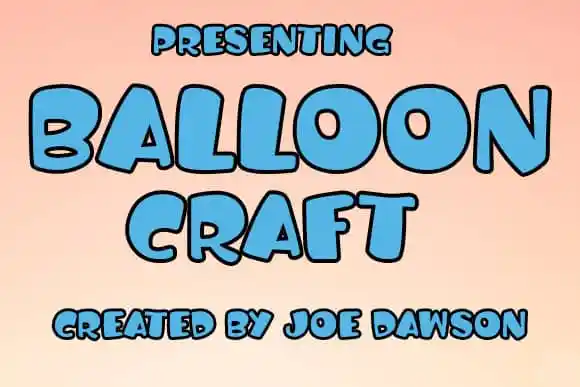
A ‘Balloon Craft Display Font’ é uma escolha perfeita para aqueles que buscam um tipo de exibição divertido e infantil para seus projetos de design. Desenvolvida pelo designer Joe Dawson na categoria de tipos de fontes de display, essa opção é ideal para adicioná-la a qualquer projeto criativo que esteja em desenvolvimento. Seus traços atemporais e sua aparência alegre garantem que ela se destaque entre o resto dos designs. Perfeito para iluminar projetos escolares ou projetos voltados à infância, essa fonte é uma ótima maneira de dar um toque criativo ao seu trabalho. Utilize-a em cartões de aniversário, materiais publicitários infantis, ou até mesmo em desenhos infantis – certamente ela não deixará ninguém indiferente.